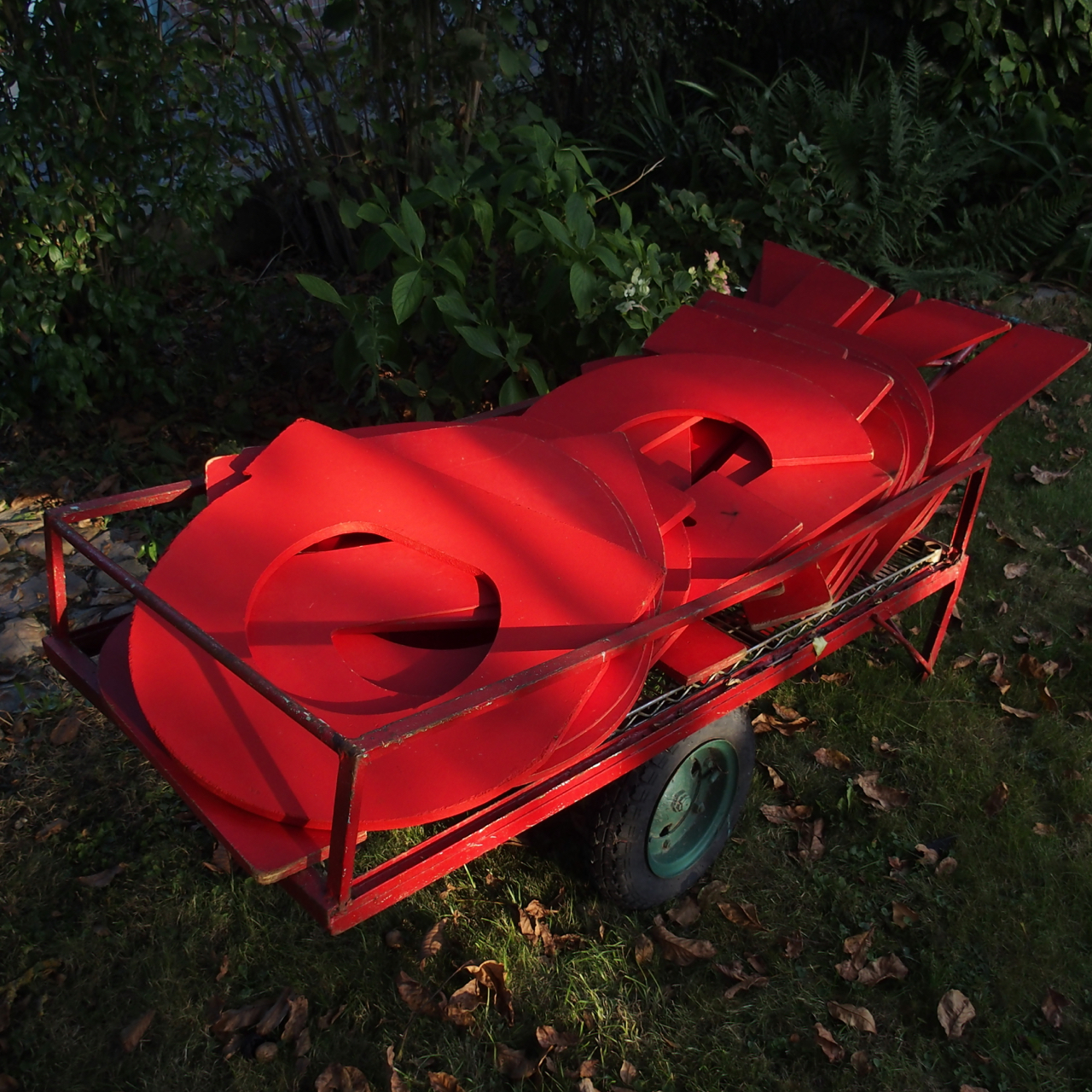
Les lettres s’usent,
en se frottant au monde.
Peut-être jusqu’au silence,
si on les frotte bien.
Correctement, complètement…
Toujours est-il que,
dans l’entre deux, souvent,
je dois les repeindre…
Et souvent, mon vieil ami William Carlos William, vient me donner du courage, rouge, en me murmurant un des plus beaux poèmes imagistes posé en mon corps bibliothèque:
So much depends
upon
a red wheel
barrow
glazed with rain
water
beside the white
chickens
Ce jour-là manquaient les poulets, mais la brouette rouge était là…
Tant de choses
dépendent
d’une brouette
rouge
scintillante
de pluie
parmi
les poulets blancs